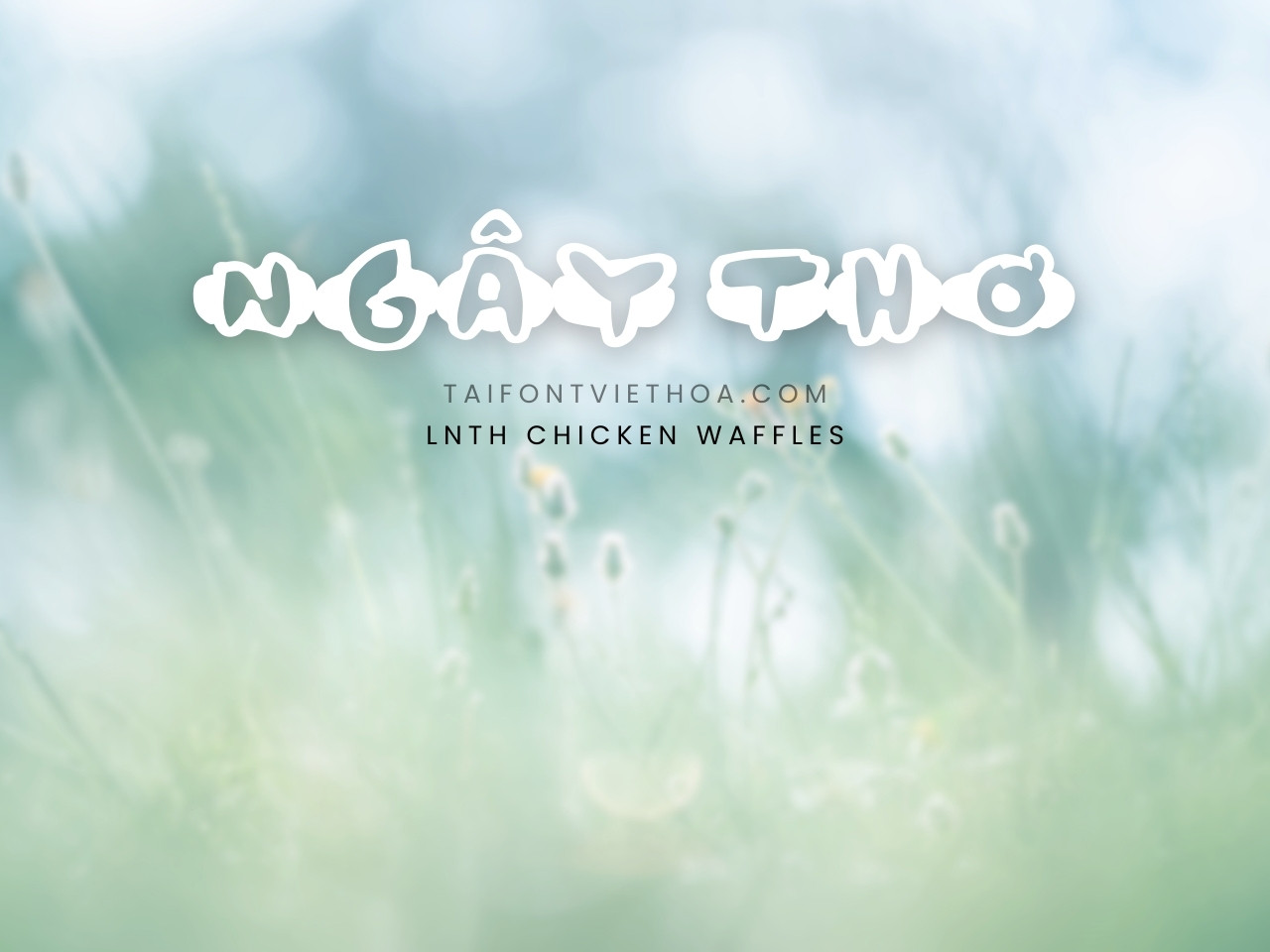
Font việt hóa LNTH Chicken Waffles
Tác giả Font: Xerographer Fonts
Giới thiệu về font Chicken Waffles
Chicken Waffles là một font chữ handwritten độc đáo với phong cách dễ thương và vui nhộn, được thiết kế bởi Misti’s Fonts – nhà thiết kế chuyên tạo ra các bộ font ngọt ngào, thân thiện và đậm chất cá nhân. Font mang đậm hơi thở tuổi thơ với những nét vẽ nguệch ngoạc mô phỏng chữ viết tay tự nhiên, gợi lên cảm giác gần gũi, giản dị và hồn nhiên. Phiên bản Việt hóa do Tuỳn Pucca thực hiện, hỗ trợ đầy đủ dấu tiếng Việt và hơn 50 ngôn ngữ khác trên thế giới, đáp ứng tốt cho các dự án đa quốc gia trong lĩnh vực sáng tạo.
Đặc điểm thiết kế và ứng dụng của font Chicken Waffles
Font Chicken Waffles có thiết kế đặc trưng bởi các đường nét tròn trịa, không đều nhau một cách chủ ý, tạo cảm giác sinh động và tự nhiên như được viết bằng bút lông. Các ký tự viết thường với phần đầu và chân chữ bo tròn, thể hiện sự thân thiện và ngẫu hứng. Font không có ligature phức tạp, dễ sử dụng trong nhiều trình biên tập đồ họa khác nhau.
Nhờ phong cách vui tươi và gần gũi, Chicken Waffles rất phù hợp cho các thiết kế dành cho trẻ em, giáo dục mầm non, blog cá nhân, sticker, sản phẩm thủ công, thiệp chúc mừng hoặc banner truyền thông trên mạng xã hội. Ngành nghề phù hợp bao gồm giáo dục, thực phẩm, sản phẩm gia đình, ngành sáng tạo và lĩnh vực quảng cáo thân thiện.